Tạo font chữ viết tay là một cách tuyệt vời để cá nhân hóa các thiết kế của bạn, từ thiệp cưới, logo, đến các ấn phẩm quảng cáo. Trong bài viết này, summerland sẽ hướng dẫn chi tiết cách tạo font chữ viết tay miễn phí, đẹp mắt bằng phần mềm chuyên dụng. Bạn sẽ có thể sở hữu một bộ font chữ độc quyền, mang đậm dấu ấn cá nhân mà không cần phải chi tiền cho các gói cao cấp.
Tóm tắt các bước tạo font chữ viết tay
- Chuẩn bị mẫu chữ viết tay: Viết mẫu trên giấy hoặc trực tiếp trên máy tính.
- Quét hoặc chụp ảnh mẫu: Đảm bảo hình ảnh rõ nét, độ phân giải cao.
- Chọn phần mềm tạo font: Sử dụng phần mềm chuyên dụng như Calligraphr, Fontstruct, hoặc Inkscape.
- Tạo file template: Tải và in template có sẵn trên phần mềm.
- Viết vào template: Điền các ký tự vào ô trống theo mẫu.
- Quét và tải lên: Quét ảnh đã viết và tải lên phần mềm.
- Chỉnh sửa và xuất file: Điều chỉnh các chi tiết và xuất file font.
Giới thiệu về font chữ viết tay
Font chữ viết tay là gì?
Font chữ viết tay là một loại font chữ được tạo ra từ chính nét chữ viết tay của một người. Khác với các font chữ in sẵn, font chữ viết tay mang đậm dấu ấn cá nhân, thể hiện phong cách và cảm xúc riêng biệt. Chúng thường được sử dụng trong các thiết kế cần sự ấm áp, thân thiện và độc đáo.
Ứng dụng của font chữ viết tay
Font chữ viết tay có thể được sử dụng trong nhiều lĩnh vực khác nhau:
- Thiết kế thiệp cưới: Tạo cảm giác ấm áp, lãng mạn.
- Logo thương hiệu: Thể hiện sự độc đáo và cá tính.
- Quảng cáo và marketing: Gây ấn tượng mạnh mẽ với khách hàng.
- Thiết kế sản phẩm: In lên các vật phẩm như cốc, áo, túi xách.
- Thiết kế web và ứng dụng: Tạo điểm nhấn cho các giao diện.
Công cụ và phần mềm cần thiết
Calligraphr
Calligraphr là một trong những phần mềm tạo font chữ viết tay phổ biến nhất hiện nay. Đây là một công cụ trực tuyến miễn phí, cho phép bạn tải lên mẫu chữ viết tay và tự động chuyển đổi thành font chữ.
Tính năng nổi bật:
- Có thể tùy chỉnh các ký tự và khoảng cách.
Fontstruct
Fontstruct là một công cụ tạo font chữ dựa trên hình học. Mặc dù không chuyên về font chữ viết tay, nhưng bạn có thể sử dụng nó để tạo các font chữ có phong cách viết tay.
Tính năng nổi bật:
- Giao diện trực quan, dễ học.
- Hỗ trợ tạo font chữ từ các hình khối cơ bản.
Inkscape
Inkscape là một phần mềm đồ họa vector miễn phí, mạnh mẽ. Bạn có thể sử dụng nó để vẽ và tạo font chữ viết tay một cách linh hoạt.
Tính năng nổi bật:
- Có thể tùy chỉnh chi tiết từng nét vẽ.
Hướng dẫn chi tiết cách tạo font chữ viết tay
Bước 1: Chuẩn bị mẫu chữ viết tay
Trước tiên, bạn cần chuẩn bị một mẫu chữ viết tay đẹp. Bạn có thể viết mẫu trên giấy hoặc trực tiếp trên máy tính bằng bút stylus.
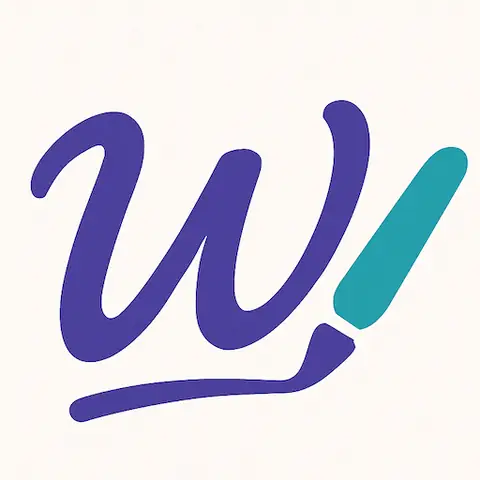
Lưu ý:
- Viết rõ ràng, đều nét.
- Đảm bảo các ký tự có kích thước tương đương nhau.
- Viết đủ các ký tự: chữ cái in hoa, in thường, số, dấu câu.
Bước 2: Quét hoặc chụp ảnh mẫu
Sau khi có mẫu chữ, bạn cần quét hoặc chụp ảnh mẫu. Đảm bảo hình ảnh rõ nét, độ phân giải cao để phần mềm có thể nhận diện chính xác.
Gợi ý:
- Sử dụng máy quét có độ phân giải 300 DPI.
- Nếu chụp ảnh, hãy sử dụng ánh sáng tốt và tránh bóng đổ.
Bước 3: Chọn phần mềm tạo font
Trong bài viết này, chúng tôi sẽ sử dụng Calligraphr để hướng dẫn chi tiết cách tạo font chữ viết tay.
Bước 4: Tạo file template
- Truy cập trang web Calligraphr.
- Đăng ký tài khoản miễn phí.
- Tạo một dự án mới và tải về file template.
Bước 5: Viết vào template
- In file template ra giấy.
- Viết các ký tự vào các ô trống theo mẫu.
- Đảm bảo viết đều nét và rõ ràng.
Bước 6: Quét và tải lên
- Quét ảnh đã viết và lưu dưới định dạng PNG hoặc JPEG.
- Đăng nhập vào tài khoản Calligraphr.
- Tải lên file ảnh đã quét.
Bước 7: Chỉnh sửa và xuất file
- Calligraphr sẽ tự động nhận diện các ký tự.
- Kiểm tra và chỉnh sửa các ký tự nếu cần.
- Tùy chỉnh khoảng cách giữa các ký tự.
- Xuất file font dưới định dạng TTF hoặc OTF.
Tùy chỉnh font chữ
- Khoảng cách: Điều chỉnh khoảng cách giữa các ký tự để font chữ nhìn tự nhiên hơn.
- Độ dày: Tùy chỉnh độ dày của các nét chữ nếu phần mềm hỗ trợ.
Kết luận
Tạo font chữ viết tay là một cách tuyệt vời để cá nhân hóa các thiết kế của bạn. Với sự hỗ trợ của các phần mềm chuyên dụng như Calligraphr, Fontstruct, và Inkscape, bạn có thể dễ dàng tạo ra một bộ font chữ độc quyền, mang đậm dấu ấn cá nhân. Hy vọng bài viết này đã giúp bạn hiểu rõ hơn về cách tạo font chữ viết tay miễn phí, đẹp mắt. Hãy thử ngay và chia sẻ thành quả của bạn với summerland nhé!